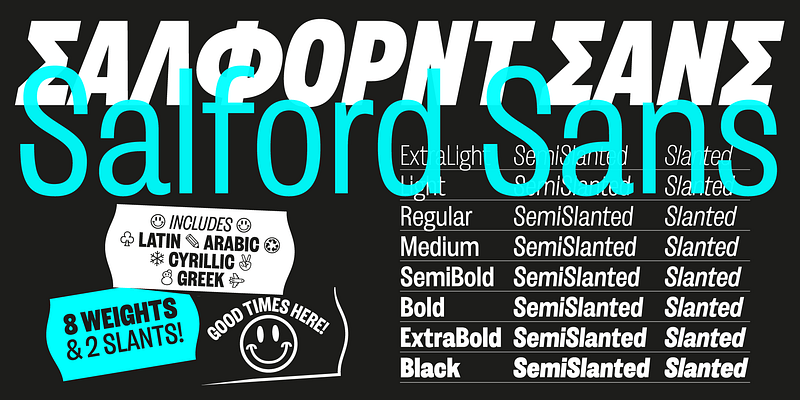
Salford Sans는 여덟 가지의 두께, 기울어진 스타일과 약간 비스듬한 기울기의 스타일을 가지고 있으며 확장 라틴어, 단조로운 그리스어, 아랍어, 키릴 문자의 4가지 문자를 포함하며, 진지하고 국제적이며 의사소통이 필요하면서도 스타일리시하고 손으로 만든 개성을 유지해야 하는 헤드라인, 에디토리얼 및 디스플레이 작업을 위해 만들어졌습니다. 기호, 깔끔한 특징, 다양한 기울기 축 및 다양한 현지 언어의 특징으로 가득 찬 Salford Sans는 전통적인 영국 스타일의 압축된 산세리프체를 기반으로 합니다. 강력하고 기능적이며 우아하게 압축된 산스이며 전 세계적으로 잘 작동하는 고전적인 아이디어에 대한 업데이트입니다.